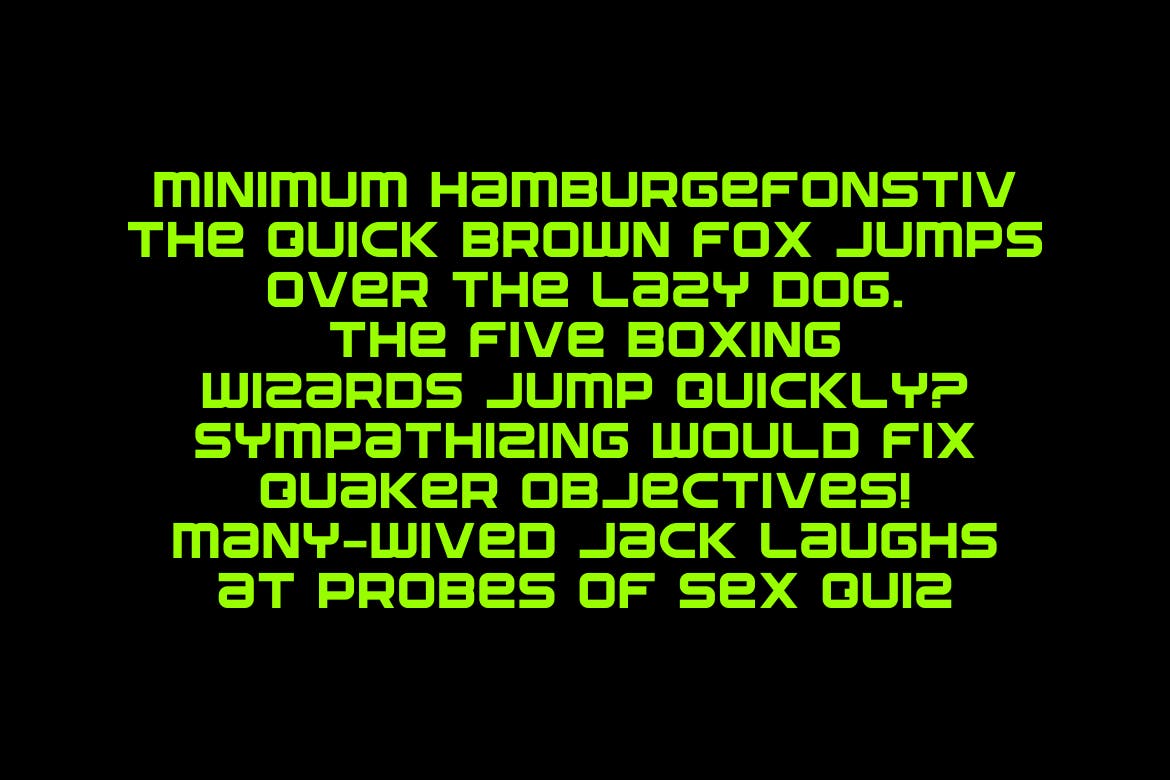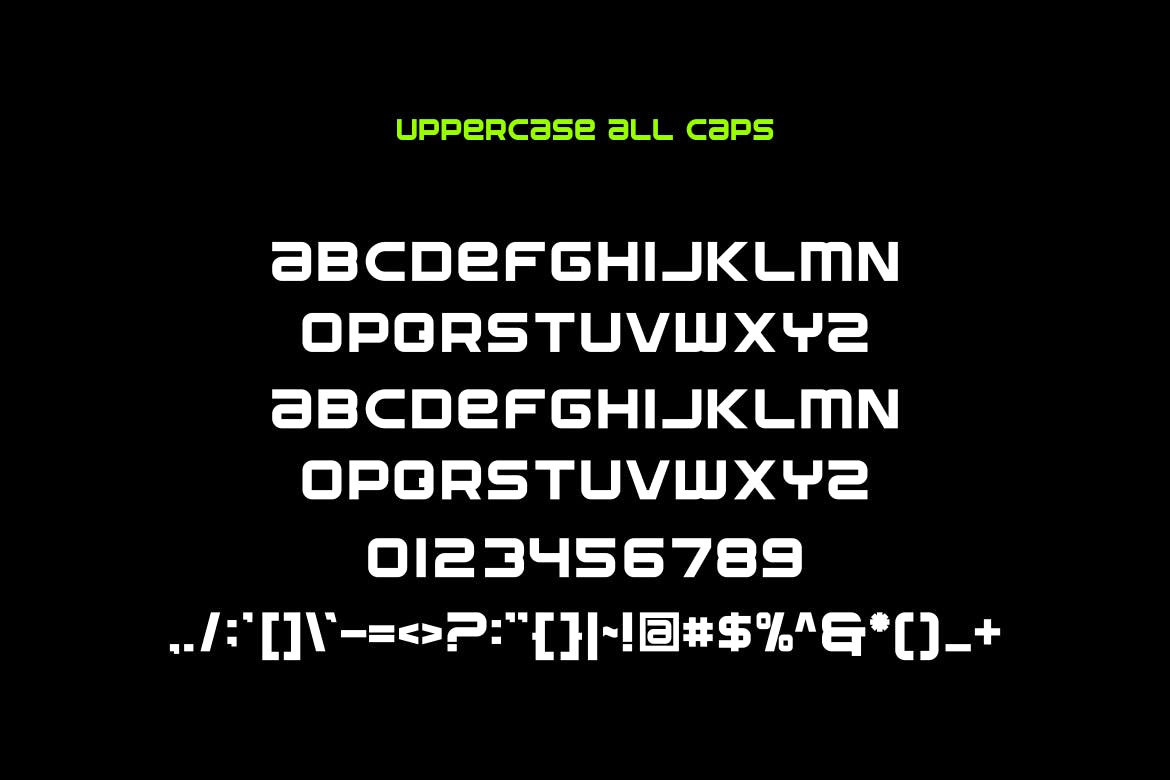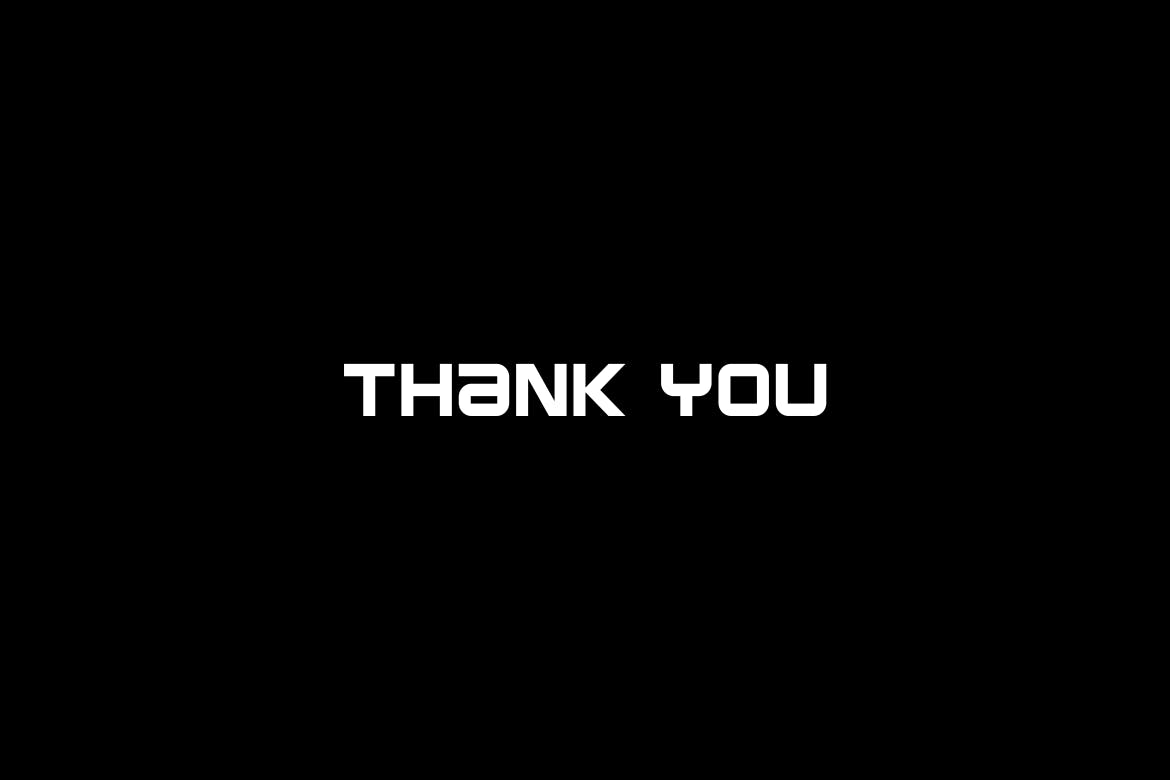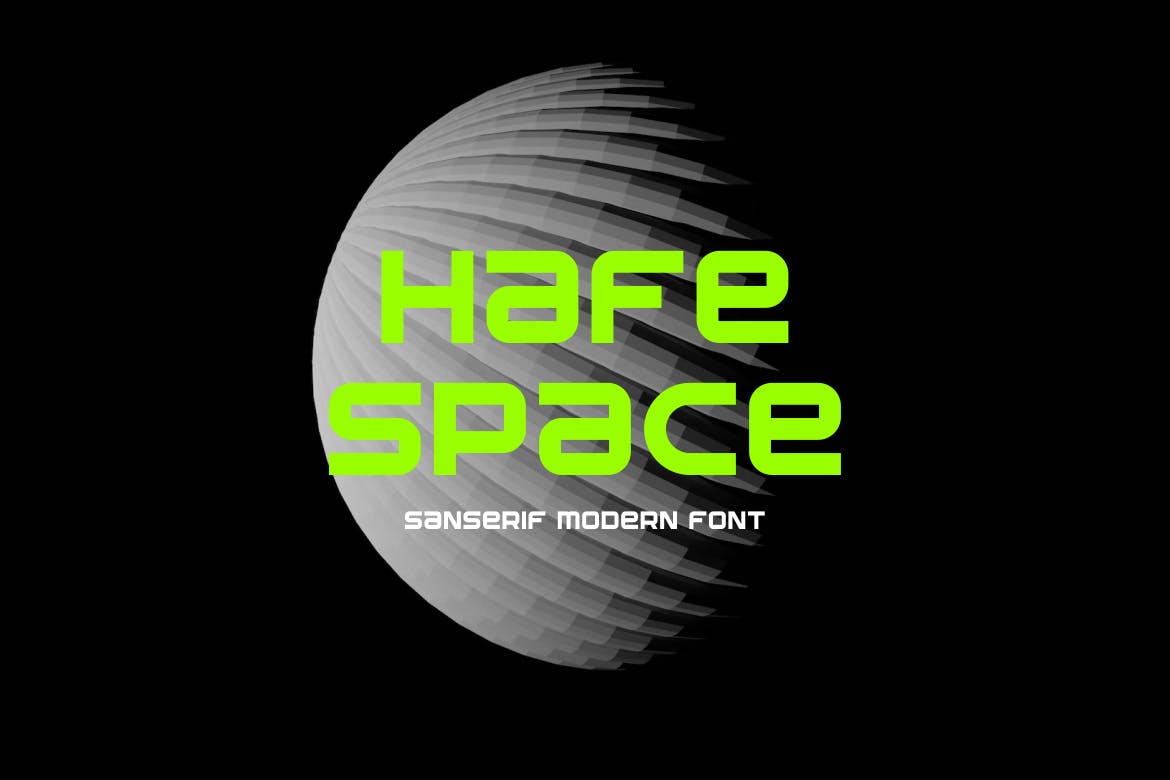
به شما عزیزان فونت جدید HafeSpace - Modern Font را معرفی میکنیم. این فونت مدرن و برجسته، برای استفاده در پروژههای برندینگ مانند لوگو بسیار مناسب است و در زمینههای مختلف به خوبی عمل میکند.